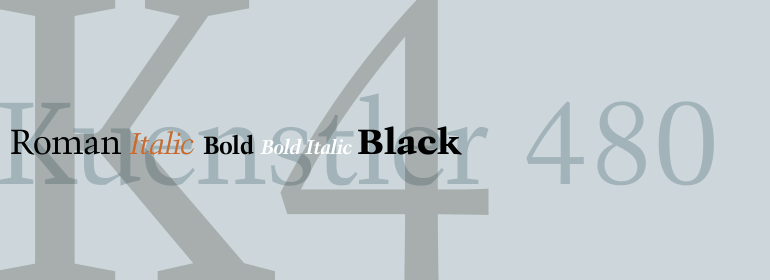
Kuenstler 480
Kuenstler 480,这款字体结构工整、笔画清晰,兼顾美观与易读性,适用于标题、正文、海报、包装、LOGO 等多种场景。字形优雅稳定,风格百搭耐看,适配日常排版与创意设计,让文字呈现更舒适、更具质感。Kuenstler 480一笔一画,皆是细节,以均衡的比例、流畅的线条打造舒适视觉体验,字形端正大气,风格简约现代。无论是商业设计、品牌宣传还是日常排版,都能轻松驾驭,让文字更有格调与力量。Kuenstler 480字体下载。